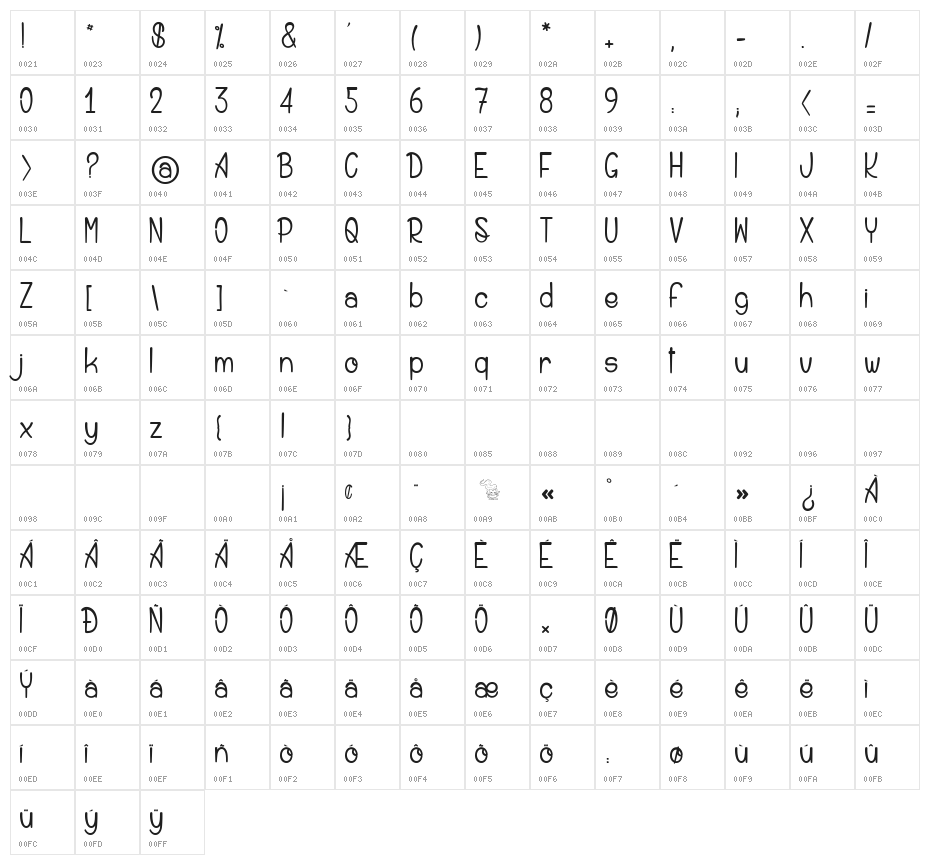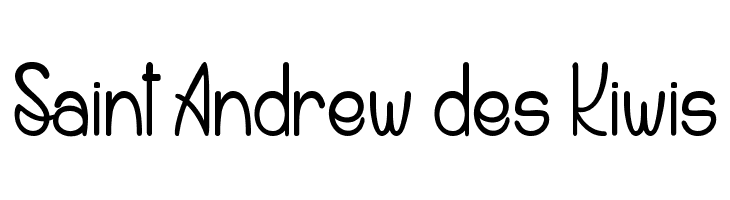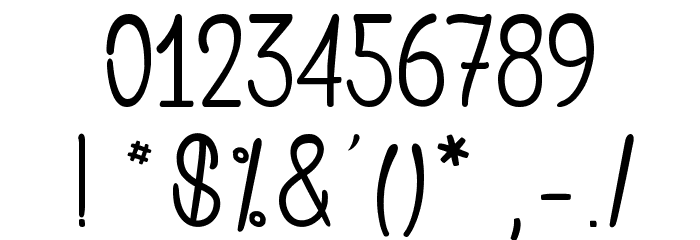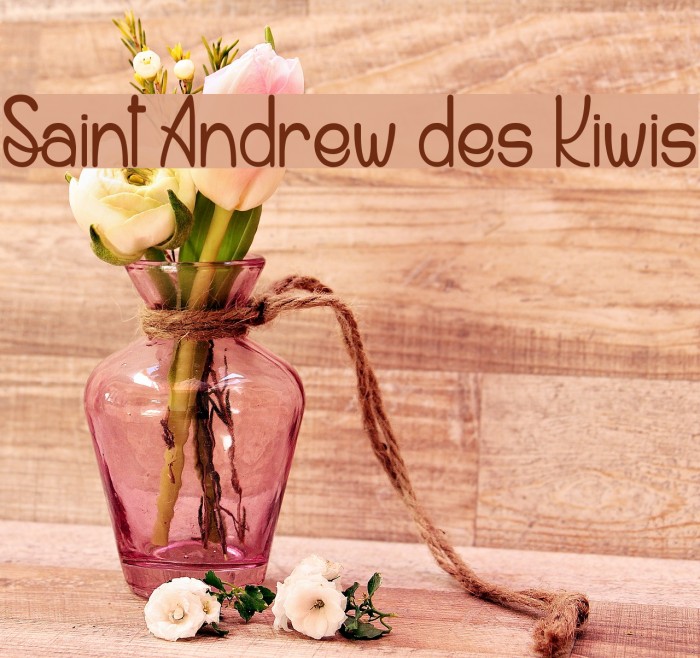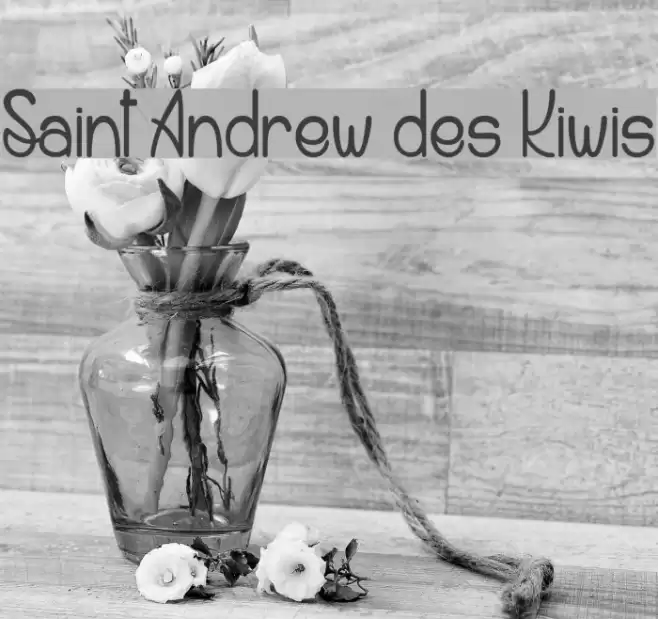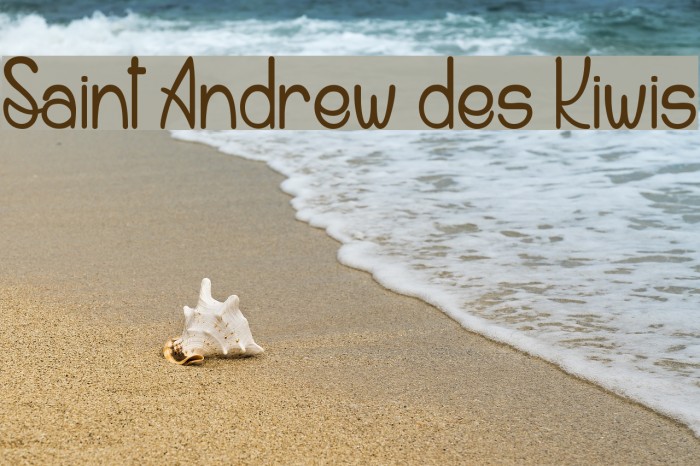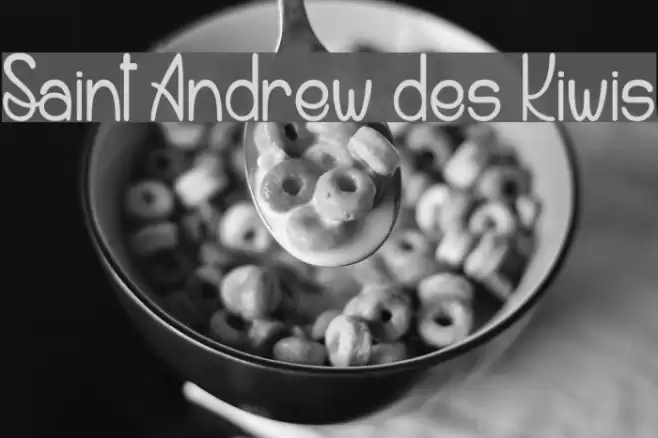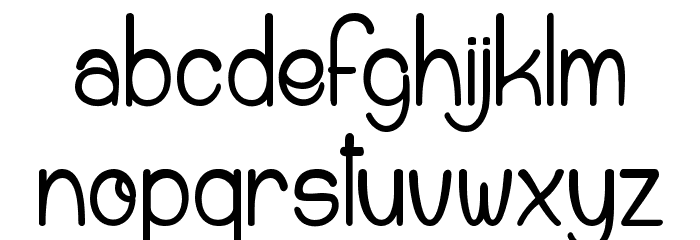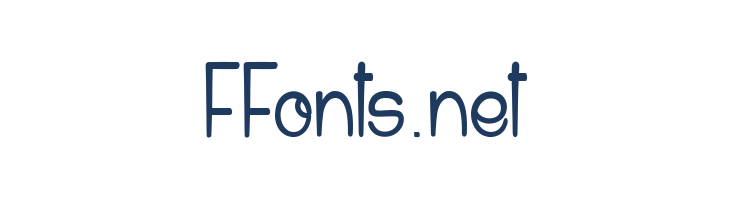
Saint Andrew des Kiwis Font
| Style général | Whimsical |
| Projets proposés | Ideal for children's books, greeting cards, playful branding, and creative posters. |